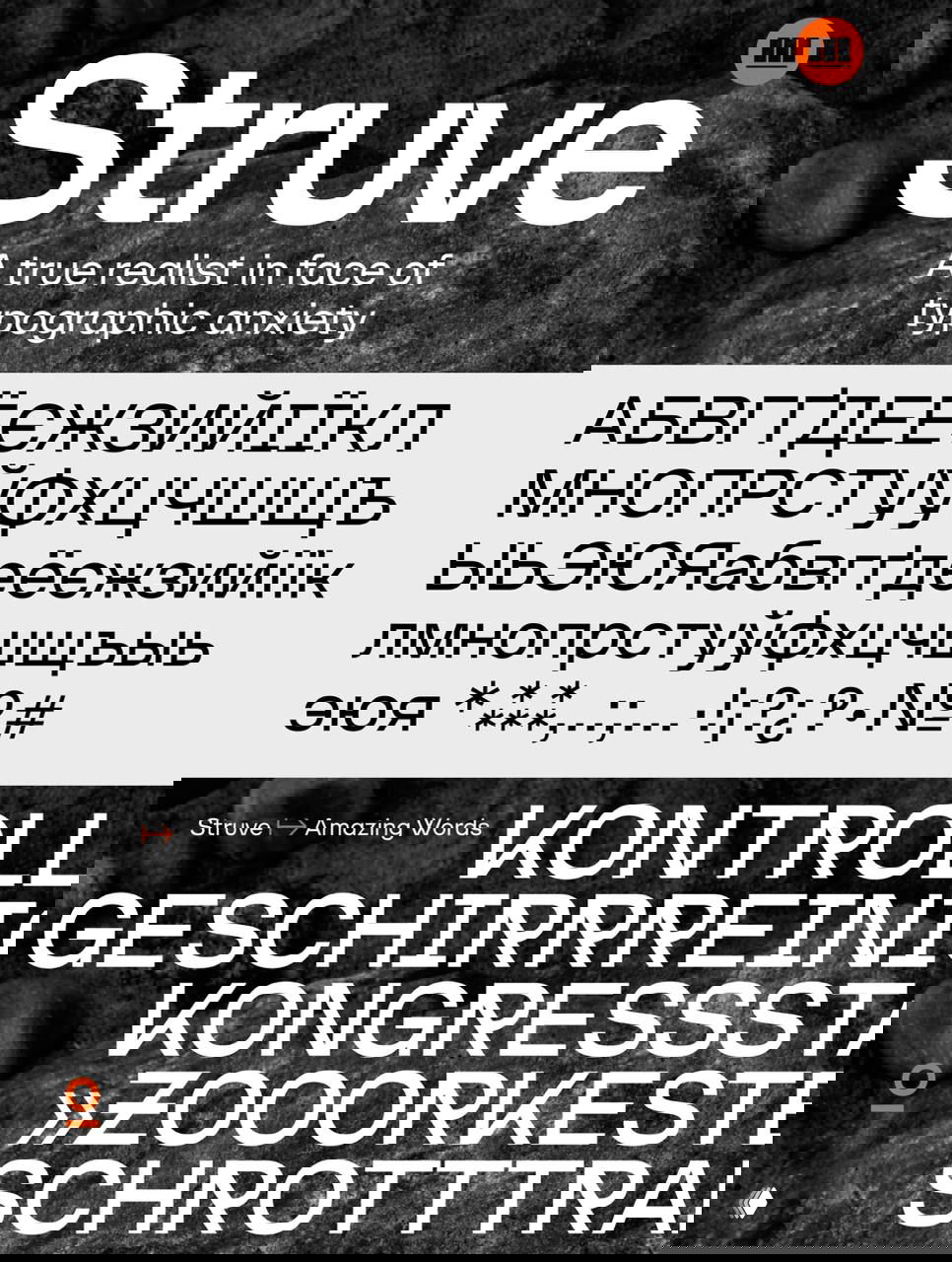
Выразительный геометрический шрифт, вдохновлённый промышленными гротесками начала ХХ века. Содержит пять вариантов насыщенности от Light до Bold.
Касса знаков включает девять комплектов стилистических альтернатив, чувствительные к регистру символы, стандартные и контекстуальные лигатуры, прописные и табличные цифры, дроби, знаменатели, числители и другие символы.